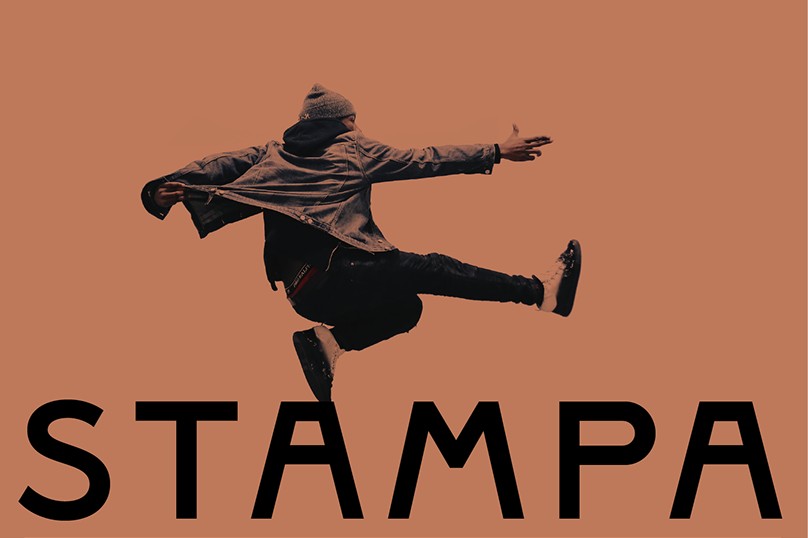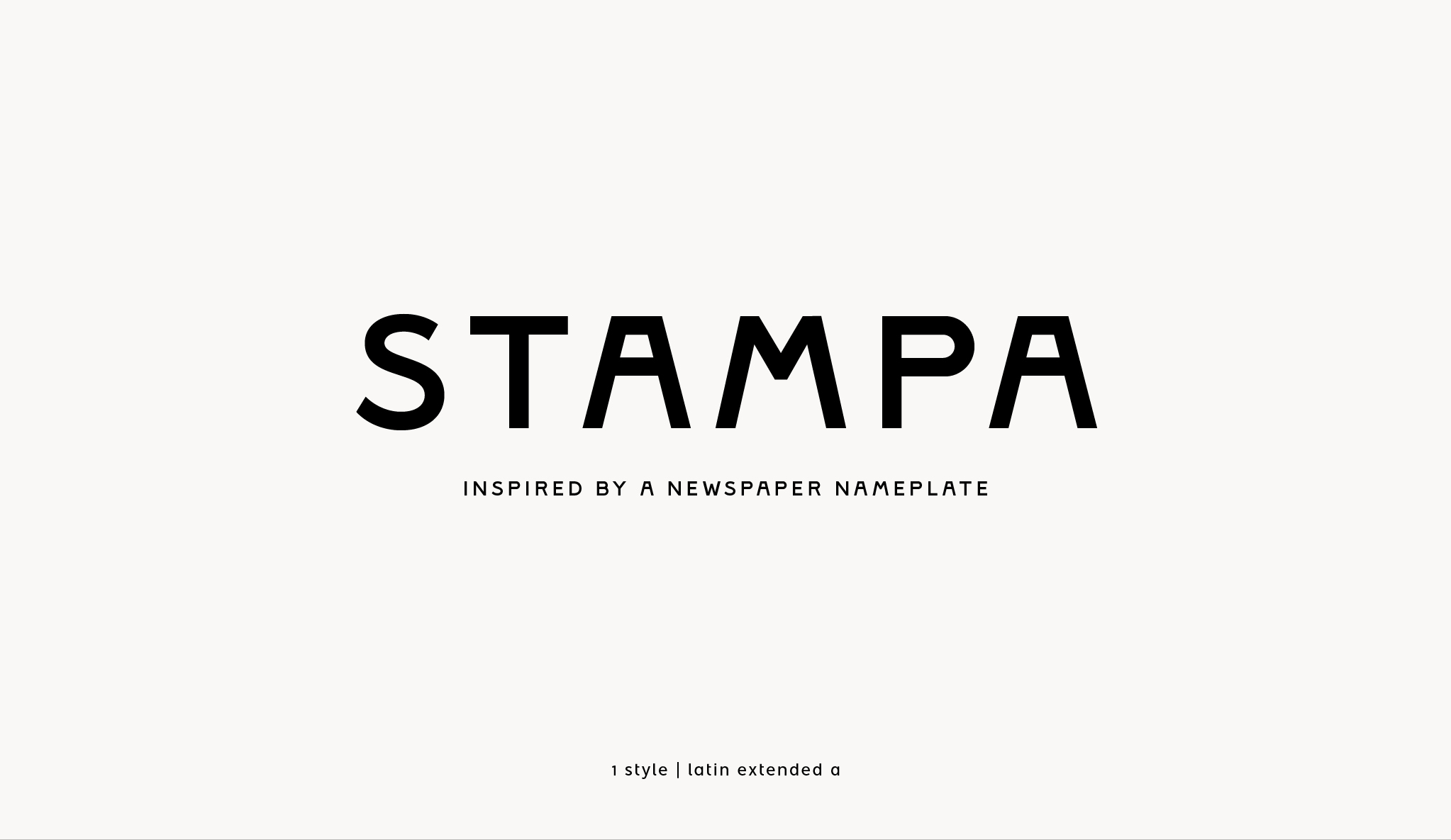
Font Stampa
Designer thiết kế logo hay bao bì phong cách quân đội, logistics thường gặp rắc rối vì font Stampa bị lỗi dấu tiếng Việt hoặc đường nét Stencil bị nhòe khi in khổ lớn. Điều này làm giảm tính mạnh mẽ và sự uy tín của thương hiệu. Xưởng In Viva cung cấp bản font Stampa Việt hóa sắc nét, đã tối ưu đường path hỗ trợ in ấn và cắt bế decal chuyên nghiệp nhất.
Font Stampa là gì?
Stampa là một phông chữ thuộc dòng Stencil (chữ đục khuôn) mang phong cách công nghiệp, cứng cáp và đầy uy lực. Đặc trưng của Stampa là các nét chữ được chia cắt bởi những khoảng hở nhỏ, gợi nhắc đến những bản khắc phun sơn trên hòm container, thùng gỗ vận chuyển hoặc trang phục quân đội. Đây là sự lựa chọn tuyệt vời cho thiết kế logo ngành vận tải, bao bì thiết bị kỹ thuật hoặc các quán cafe mang phong cách “bụi bặm”, phá cách.
Ưu điểm của Stampa là khả năng nhận diện cực cao từ khoảng cách xa. Tuy nhiên, cấu trúc chia cắt nét của Stampa rất kén bảng mã tiếng Việt. Nếu không xử lý chuẩn, các dấu mũ sẽ làm mất đi tinh thần Stencil đặc trưng. Bản font Stampa Việt hóa tại In Viva đã được căn chỉnh tỉ mỉ, đảm bảo các dấu thanh luôn đồng bộ với các khoảng hở của bộ chữ gốc, mang lại vẻ ngoài hoàn mỹ cho ấn phẩm truyền thông của bạn.
Stampa font không chân
Lưu ý: Với font Stampa, bạn nên sử dụng hệ màu đơn sắc như đen, trắng hoặc xanh rêu để tôn vinh sự mạnh mẽ, tối giản của phông chữ này trên bao bì.
Vẻ ngoài cứng cáp của Stampa giúp các sản phẩm trở nên cá tính và bền vững hơn:
• Thiết kế bao bì hộp gỗ: Stampa cực kỳ phù hợp để khắc laser hoặc in lụa trên các hộp rượu gỗ, hộp trà, tạo vẻ ngoài cao cấp và chắc chắn cho sản phẩm tặng đối tác.
• Sản xuất túi giấy Kraft in logo Logistics: Chữ Stampa in đen đặc trên nền túi Kraft nâu tạo nên phong cách tối giản, hiện đại và vô cùng chuyên nghiệp.
• In ấn bộ sản phẩm công nghệ: Logo dùng font Stampa in UV trên sạc dự phòng kim loại hoặc loa bluetooth mang lại vẻ ngoài kỹ thuật, mạnh mẽ và nam tính.
• Trang trí biển hiệu showroom phong cách Loft: Sử dụng định dạng vector để cắt bế mica dán tường, tạo điểm nhấn ấn tượng cho không gian trưng bày sản phẩm.
Stampa font
Sử dụng font chữ Stampa cần lưu ý gì?
Để bản in sử dụng font Stampa đạt độ sắc sảo cao nhất, designer cần nắm rõ các kỹ thuật sau:
• Kiểm soát các khoảng hở Stencil: Khi in kích thước siêu nhỏ, các khoảng hở giữa nét chữ có thể bị mực tràn làm bít kín. Bạn nên nới rộng font một chút để giữ nguyên đặc trưng của bộ chữ.
• Lựa chọn công nghệ in lụa: Với font Stampa, in lụa sẽ giúp lớp mực dày và nổi bật hơn trên các bề mặt thô nhám của thùng carton hay gỗ.
• Lưu ý độ tương phản: Font Stampa cần độ tương phản màu sắc cao giữa chữ và nền để đạt hiệu quả đọc tốt nhất cho người xem.
Stampa font hiện đại